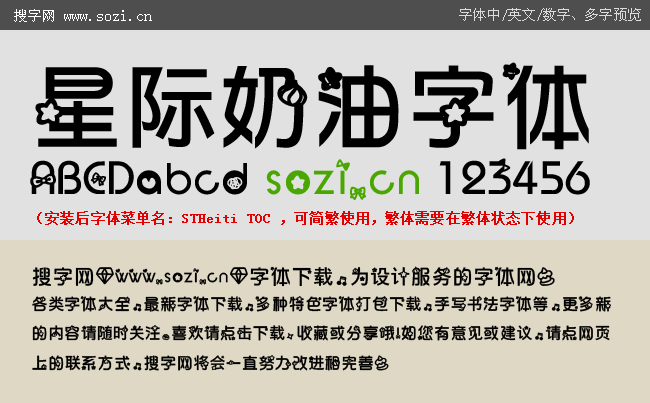
星際奶油字體
搜字網(wǎng)給大家提供一款星際奶油字體手機(jī)中文字體下載。這款手機(jī)字體是一款POP風(fēng)格的卡通字體,字體間嵌入了卡通星星圖案,連標(biāo)點(diǎn)也變成了可愛的卡通圖形,是非?蓯鄣囊豢钭煮w,特別適合喜歡手機(jī)字體個(gè)性一些的朋友在手機(jī)上安裝使用。